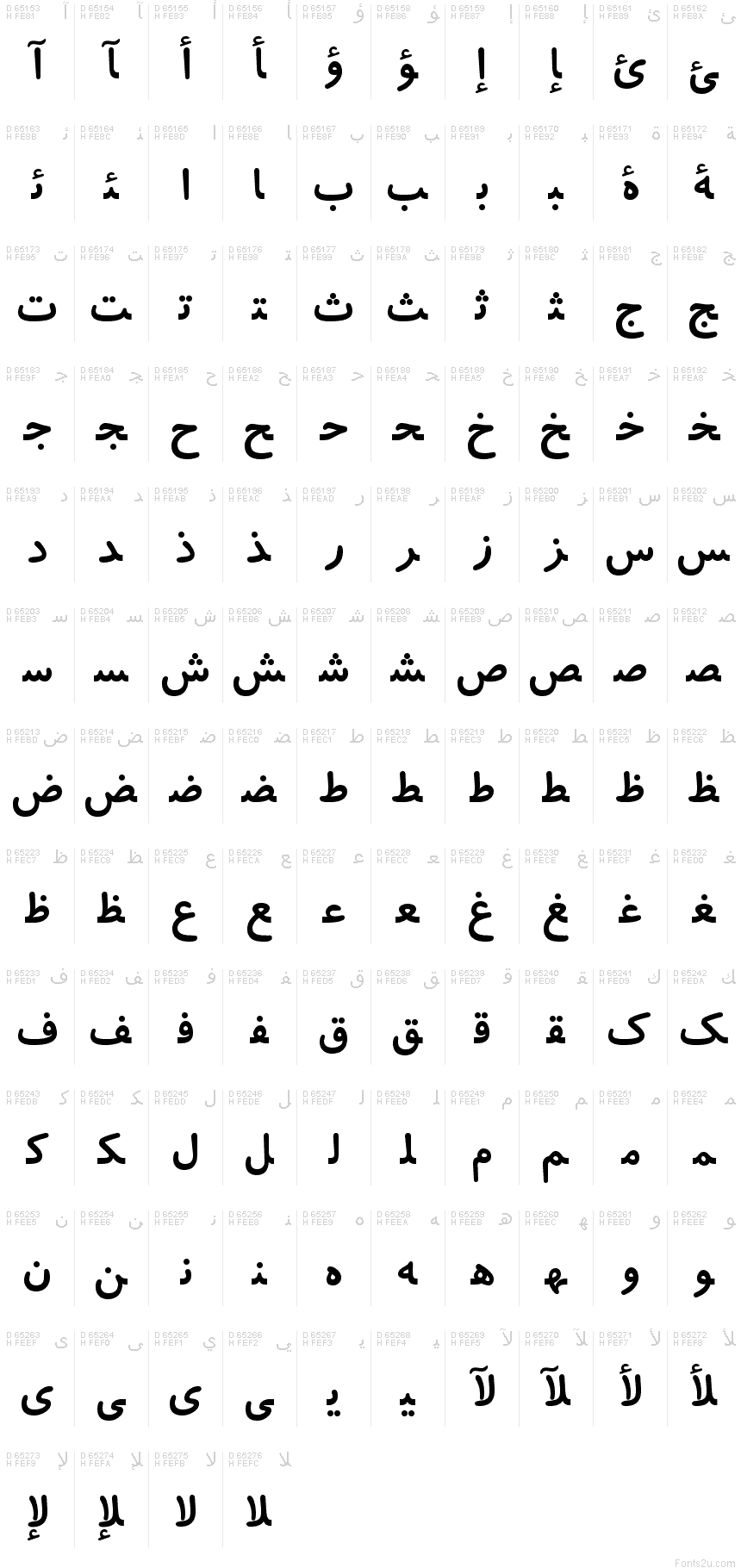
B Koodak Bold von Borna Rayaneh ist eine kostenlose arabische Display-Schrift mit einem abgerundeten, freundlichen Rhythmus. Die Buchstaben wirken weich und kompakt, mit fließenden Verbindungen und einem leicht verspielten Schwung, der die Schrift warm statt formell erscheinen lässt.
Dadurch eignet sie sich ideal für Kinderpublikationen, Lehrmaterialien, Verpackungen, App-Banner und Grafiken für kulturelle Veranstaltungen, bei denen eine sanftere arabische Anmutung gefragt ist. Als kostenlose Schrift eignet sie sich zudem hervorragend für kurze Schlagzeilen, Titelkarten und logoartige Schriftzüge, da die breiten Kurven und engen Verbindungen selbst kurzem Text eine ruhige und nahbare Ausstrahlung verleihen.